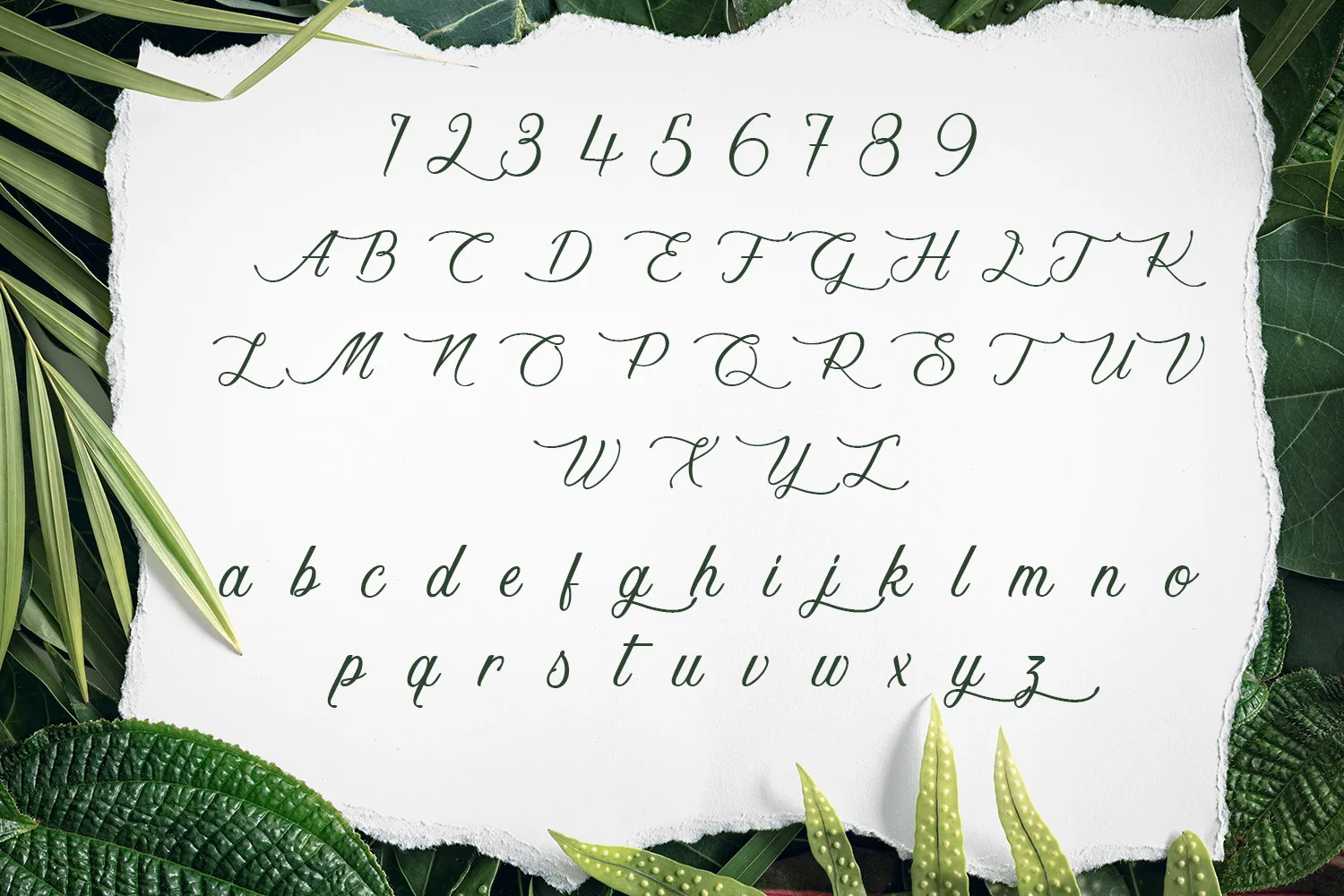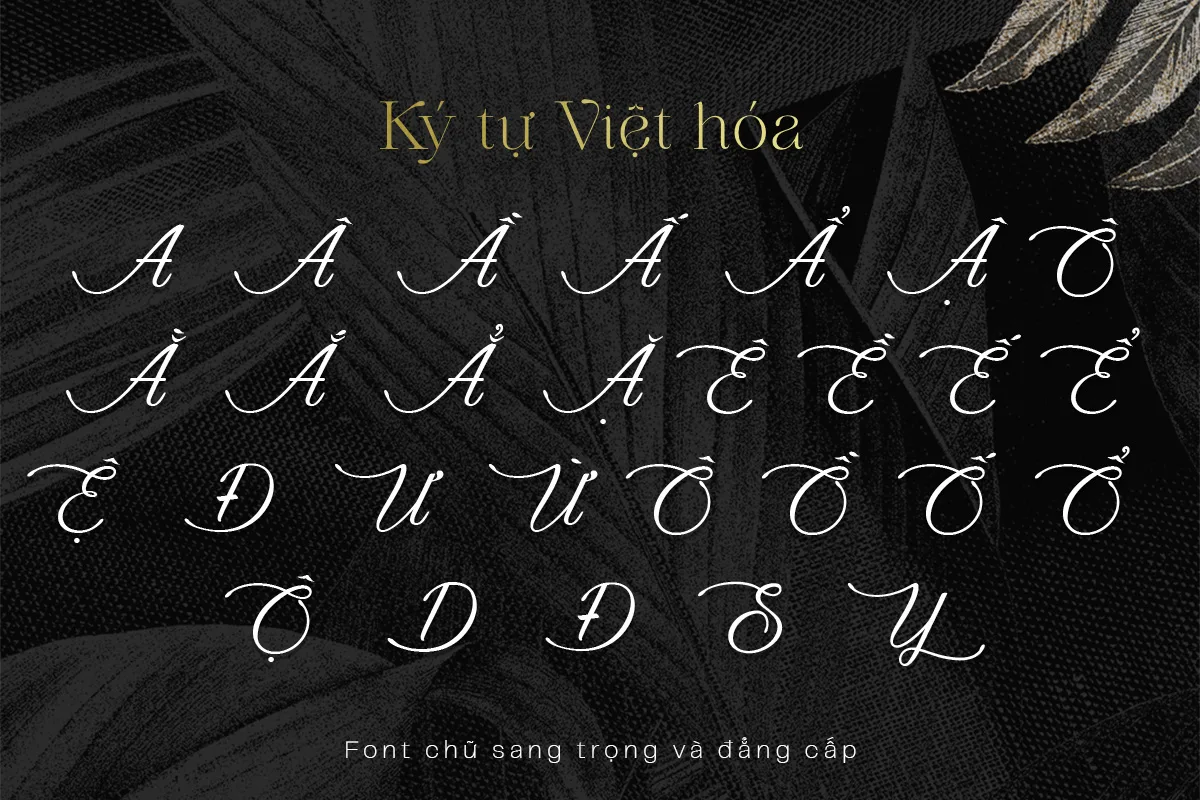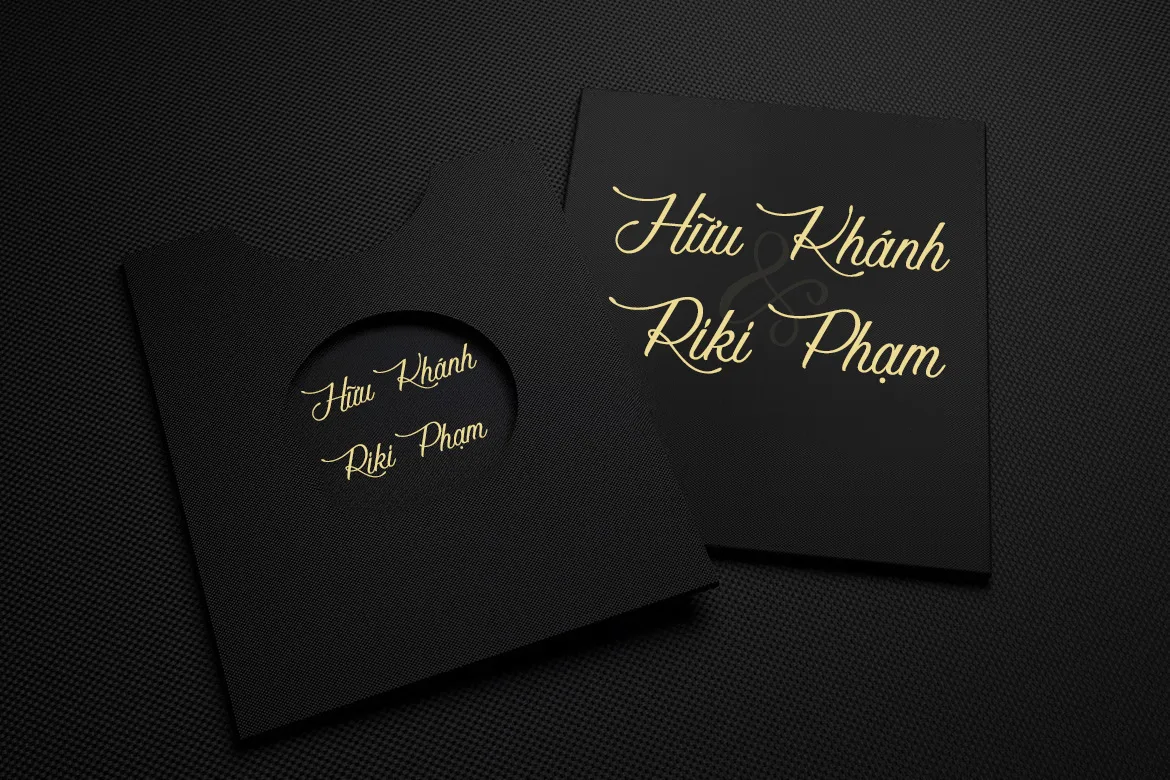
DVN Scriptorial Việt hóa – Font chữ Viết tay trang nhã, thanh lịch phù hợp cho chữ ký, thiệp mời cần sự trang trọng
Font DVN Scriptorial Việt hóa là một kiểu chữ viết tay thanh lịch, mang nét đẹp mềm mại và cổ điển. Bộ chữ được thiết kế với đường cong uyển chuyển, phù hợp cho các ấn phẩm mang phong cách trang trọng như thiệp mời, tiêu đề trang, chữ ký cá nhân hay thiết kế nữ tính.
Phiên bản Việt hóa được làm lại dấu chuẩn, giữ nguyên chất thơ và sự bay bướm trong từng con chữ, hỗ trợ đầy đủ tiếng Việt. Với phong cách sang trọng nhưng dễ đọc, DVN Scriptorial là lựa chọn lý tưởng cho các dự án cần sự tinh tế và cảm xúc.